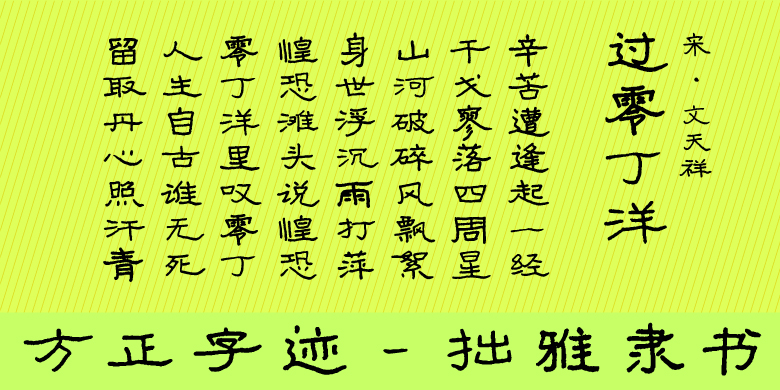
方正字迹-拙雅隶书
字体品牌: 方正字迹 设计师: 高俭 字体分类: 常规书写·硬笔 字体属性: 精品字 字符集: 大陆简体(GB2312-80) 发布时间: 2023
该字库采用硬笔书写,融合《张迁碑》、《曹全碑》、《乙瑛碑》等汉隶风格,结字巧中有拙,一任天然,拙朴中自带典雅风范。承继汉隶《乙瑛碑》中正素朴的基调上,融合《张迁碑》的典雅高古、虬劲有力,犹取《曹全碑》的飘逸秀气、灵动有情。字形左低右高,似一气宇轩昂的士大夫,又似一顾盼嗟叹的多情女子。笔划粗细均衡,转折处多圆润流畅,收笔处却自成锋刃,不张扬却内蕴锋芒,正如中国文人的圆滑谦和的处世之态和一身傲骨的立世之姿,柔中带刚。